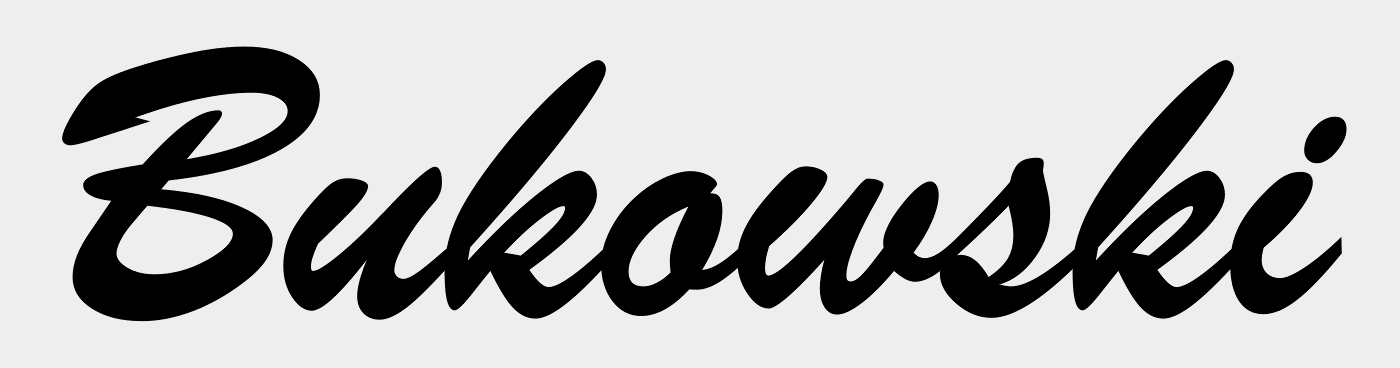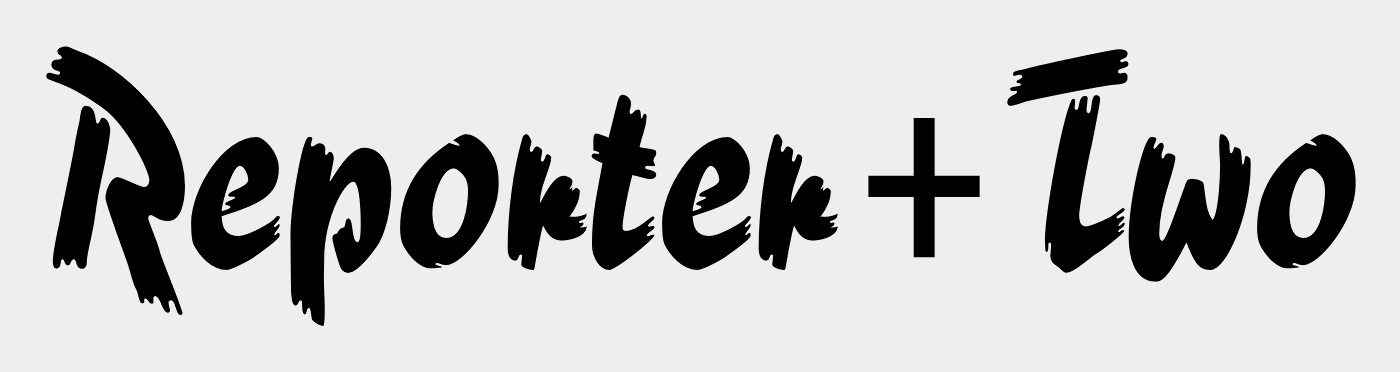
Welche Schrift ist das? (Schreibschrift)
ist mir klar, dass es sich um eine ziemlich alte schrift handeln muss.... (gehört zur Wiederherstellung eines ziemlich alten Logos - ca. ende 80er Jahre)
Die Schrift ist etwas älter und ich habe ja die Angaben schon gepostet. 1942 von Robert E. Smith im Auftrag von ITC geschnitten. Ab den 1950ern war die Schrift in Wirtschaftswunderschland sehr beliebt und hier in Karlsruhe findet man noch einiges an alten Leuchtreklamen aus den 1960ern und 1970ern mit der Brush Script. Man findet sie auch in alten Designs. Das Gegenstück dazu ist die Reporter Two von Carlos Winkow aus dem Jahr 1938. Beides sind rohe Pinselschriften aus der Zeit um 1940, aber der Verwendungszweck war jeweils ein anderer.
Kommerzielle Anwendungen wie Werbung und zeitgenössisches Design das gefällig daherschleicht und trotzdem modisch wirken sollte.
Reißerisch und aggressiver, ideal für Krimis und revolutionäre Politik. Das Schreiben an der Wand ist in dieser Schrift gestaltet.
Der glatte Kommerz der Brush Script steht der reißerischen Aufmachung der Reporter Two gegenüber. Die beiden Schriften sind exemplarische Pinselschriften und so was wie Gegenpole in der Gestaltung. Ich würde das als Basiswissen deklarieren.
Bei CorelDraw hieß die übrigens lange Banff und gehörte als WFN-Schriftart schon bei Version 1.2 zum damals noch mageren Lieferumfang.
Bei TeX/LaTeX gibt es diese Schrift als „BrushScriptX-Italic“ von Maurizio Loreti:
So ziemlich jeder sollte eine Form der Brush Script bei seiner Software dabei haben. Jeder, aber auch wirklich jeder! :nicken:
Die lächerliche Reporter-Digitalisierung hat mit dem Original nur sehr wenig zu tun, es ist eher eine Fransen- als eine Pinselschrift.
Daß man solche Schriften »braucht«, glaube ich nicht. Man sollte Schreib- als Satzschriften nur selten verwenden, weil es sich dabei um meistens mehr und gelegentlich weniger unvollkommene Imitate handelt. Man beschäftige lieber Kalligrafen.
Man sollte Schreib- als Satzschriften nur selten verwenden, weil es sich dabei um meistens mehr und gelegentlich weniger unvollkommene Imitate handelt. Man beschäftige lieber Kalligrafen.
Wir können diese häufig vorgetragene Faustregel im Jahr 2016 wirklich mal beerdigen. Sie ist schon generell fraglich, aber heute im Zuge der technischen Entwicklungen einfach überholt.
Die lächerliche Reporter-Digitalisierung hat mit dem Original nur sehr wenig zu tun, es ist eher eine Fransen- als eine Pinselschrift.
Daß man solche Schriften »braucht«, glaube ich nicht. Man sollte Schreib- als Satzschriften nur selten verwenden, weil es sich dabei um meistens mehr und gelegentlich weniger unvollkommene Imitate handelt. Man beschäftige lieber Kalligrafen.
Wirf einen Blick auf die Arbeiten aus den 1960ern und 1970ern. Für die einfachen Gebrauchsgrafiken waren diese Schriften angemessen. Nicht immer ist ein Kalligraf oder eine Kalligräfin im Budget und/oder der Zeitplanung vorgesehen.
Wir können diese häufig vorgetragene Faustregel im Jahr 2016 wirklich mal beerdigen. Sie ist schon generell fraglich, aber heute im Zuge der technischen Entwicklungen einfach überholt.
Wenn ich mir die Entwicklung so ansehen ... war ab dem erfolgreichen Aufkommen des Fotosatz bereits das Hinwegsterben dieser Faustregel aus den alten Bleisatzzeiten zu beobachten. Seit OTF haben wir da auch noch eine ganz neue Zeitrechnung und die technischen Möglichkeiten sind weit über dem, was man so im Alltag ausreizen kann. Ich muss da gerade an das Video zu Liza von Underware denken, da sieht man das schon ganz gut.
Die besten OTF-Ergänzungen können die Kalligrafie nicht ersetzen, denn der Kalligraf denkt beim Schreiben kontextuell. Kalligrafie hat etwas mit Denken und mit Schwingungen zu tun, das kann einem keine Typen-Ergänzung abnehmen. Außerdem fehlt allen digitalen Schreibschriften die gleichbleibende Strichstärke bei unterschiedlichen Schriftgrößen, die der handgeführte Pinsel und noch viel mehr die Feder aber stets beibehält. In dieser Hinsicht sind sogar Bleisatzschreibschriften den digitalen überlegen. Ich habe eine Anglaise in 60p im Kasten, die hat Haarlinien in derselben Stärke wie die Typen in 12p. Die digitalen Schreibschriften sind in großen Größen meistens klobig und in kleinen zu eng.
Daß es auch schlechter und billiger geht und meistens gemacht wird, ist auch mir bekannt. Selten setze ich auch Schreibschriften als Satzschrift ein, und dann mit Bedauern und schlechtem Gewissen. Es war schon immer eine Regel nur für Kenner und Genießer, daß man Schreibschriften nicht imitieren kann, es wurde ständig gemacht. Als Ersatz gab es aber auch Schreibschriften, die gar nicht so taten, als seien sie mit der Feder geschrieben. Schwungvollere Kursive sozusagen. Gibt es heute auch.